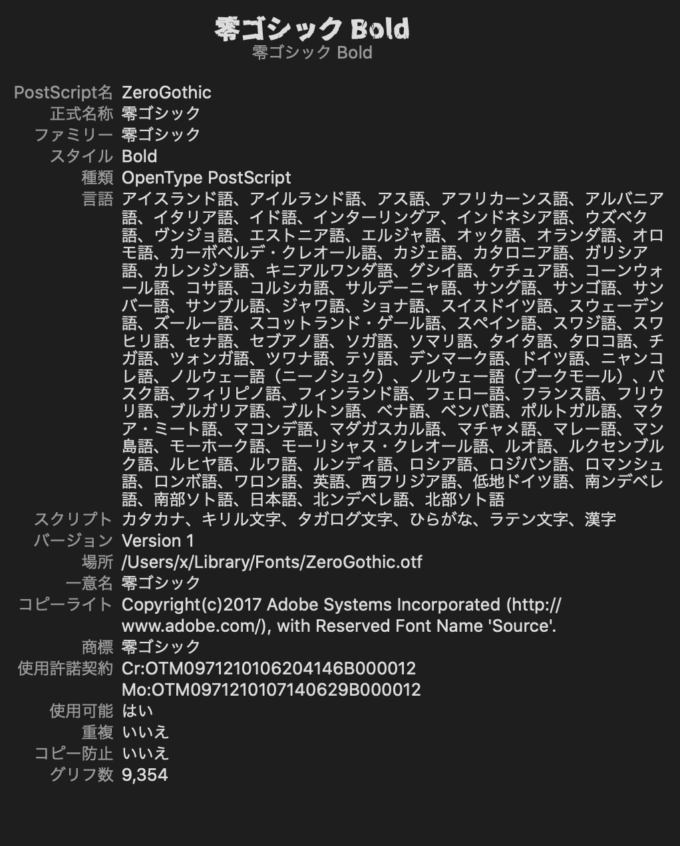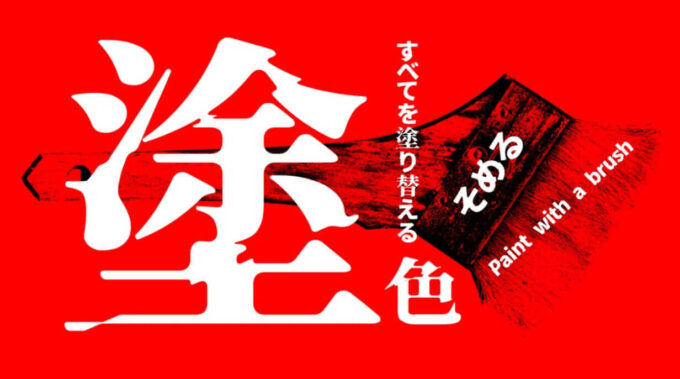
今回は癖が強めのインパクトのあるフリーフォントをまとめて紹介していきます。
インパクトのあるフリーフォントまとめ
インパクトのあるフリーフォントまとめて紹介していきます。
零ゴシック
はらませにゃんこ
ミシミシ
Wolverine
ナイショ文字
モフ字
デビルマンフォント
ぺんぎんたうん
トガリテ
アンニャントロマン
ドラえもじ
バジリスク
AGAINTS TYPEFACE
OVER DRIVE
しょかきうたげ
略字超少明朝穴
異世明・異世ゴ
Blade 2
廻募(エモ)